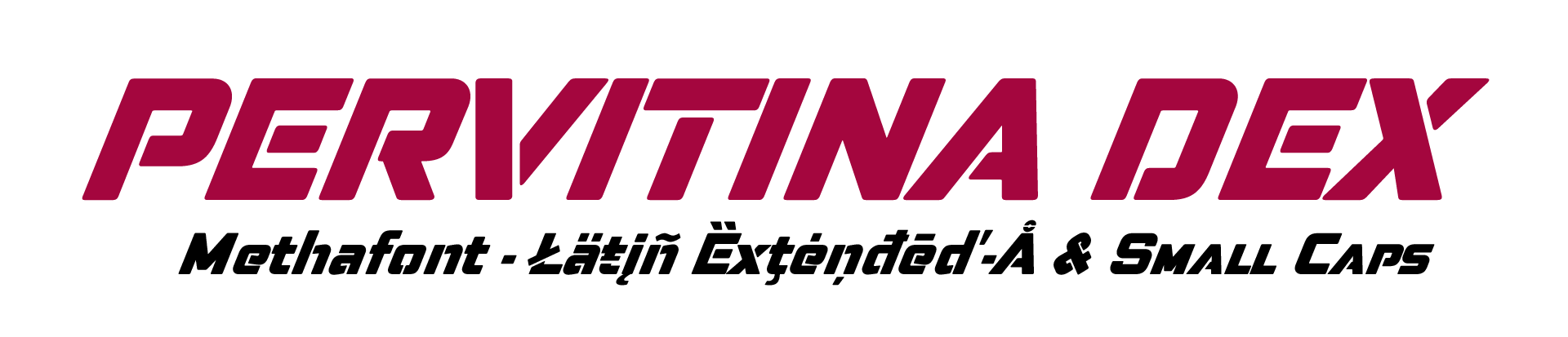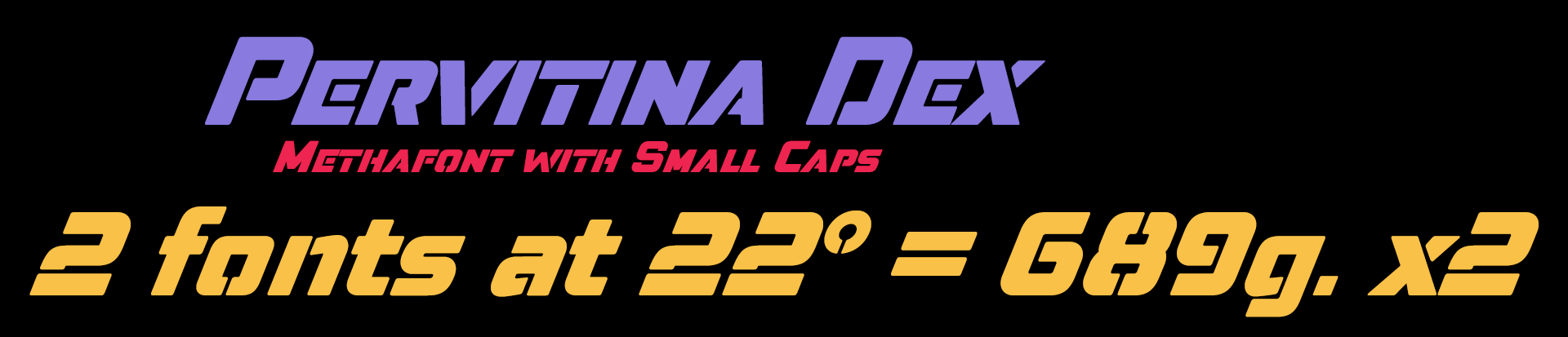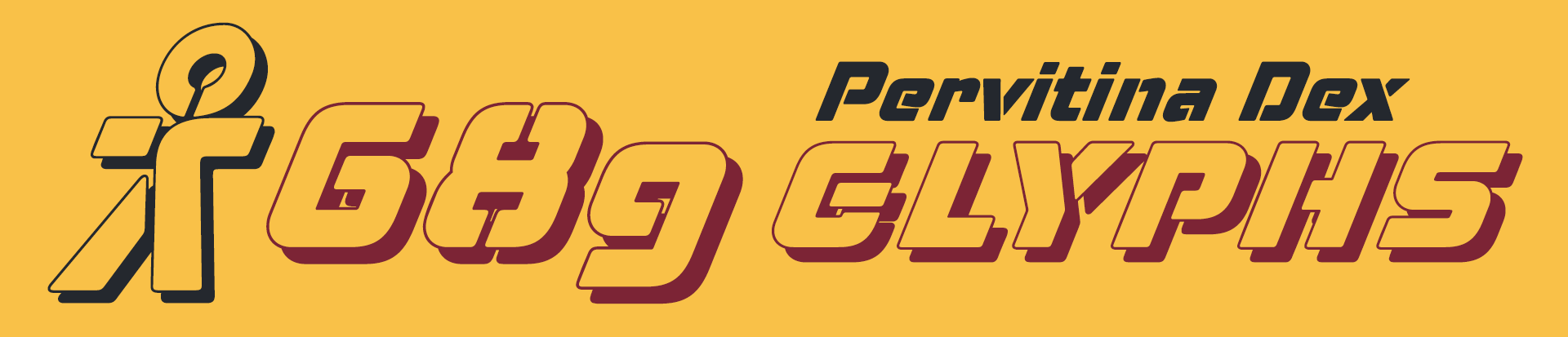
Methafont w/ Small Caps
Estilo: Sans Serif, Cursive, Techno, Stencil
Proporción: Cursiva
Glyphs: 689
Alternates: 69
Autor: deFharo
Año de publicación: 2019.
Funciones OpenType: Additional languages, All Alternates, Bitcoin, Contextual Alternates, Denominators, Discretionary Ligatures, Extended Fractions, Historical Forms, Inferiors, Kerning, Localized Forms, Numerators, Oldstyle Figures, Ordinals, Scientific Inferiors, Slashed Zero, Small Capitals, Small Capitals From Capitals, Standard Ligatures, Stylistic Set, Subscript, Superior letters, Superiors, Superscript.
• Latin Extended-A with Small Caps •
Pervitina Dex dispone de soporte completo para todos los idiomas derivados del Latín (Latin Extended-A)y funciones OpenType avanzadas para numerales, fracciones, ordinales, etc.
La tipografía Pervitina Dex dispone en su versión comercial de un juego de 689 glifos y soporte para cualquier idioma europeo o centro europeo derivados del Latín (Latin Extended-A). Pervitina Dex también incluye funciones OpenType (Compatibles con InDesign, QuarkXpress, Photoshop e Illustrator.